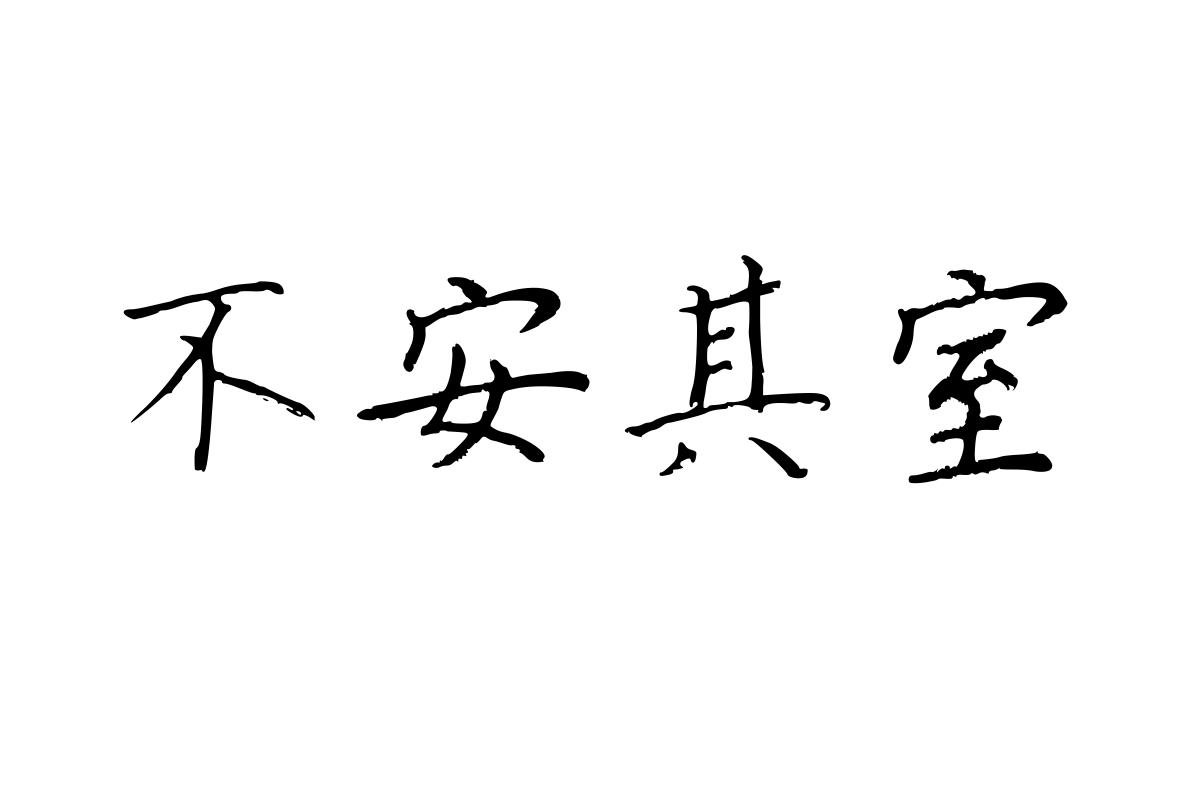
汉呈吴红生钢笔楷书是一款由汉呈公司设计的钢笔楷书字体。这款字体具有独特的风格和特点,适合用于书法、设计等领域。
1. 字形结构:汉呈吴红生钢笔楷书的字形结构紧凑,笔画粗细适中,线条流畅。整体上呈现出一种简洁、明快的感觉,给人一种清新自然的印象。
2. 字体特点:这款字体的特点在于其笔画的粗细变化和笔势的连贯性。在书写过程中,笔画的粗细变化可以更好地表达出汉字的结构和意境,使作品更具艺术感。同时,笔势的连贯性也使得书写更加流畅,提高了书写的效率和质量。
3. 适用场景:汉呈吴红生钢笔楷书适用于书法创作、设计排版等多种场合。无论是用于书写还是用于展示,这款字体都能展现出其独特的魅力。
4. 使用效果:使用汉呈吴红生钢笔楷书进行书法创作,可以展现出作者对汉字结构的理解和把握,以及书写技巧的运用。同时,这种字体也适合用于设计排版,如报纸、杂志、广告等,能够为作品增添一份独特的美感。
总之,汉呈吴红生钢笔楷书是一款具有独特风格和特点的字体,适用于多种场合,能够为作品增添一份独特的美感。